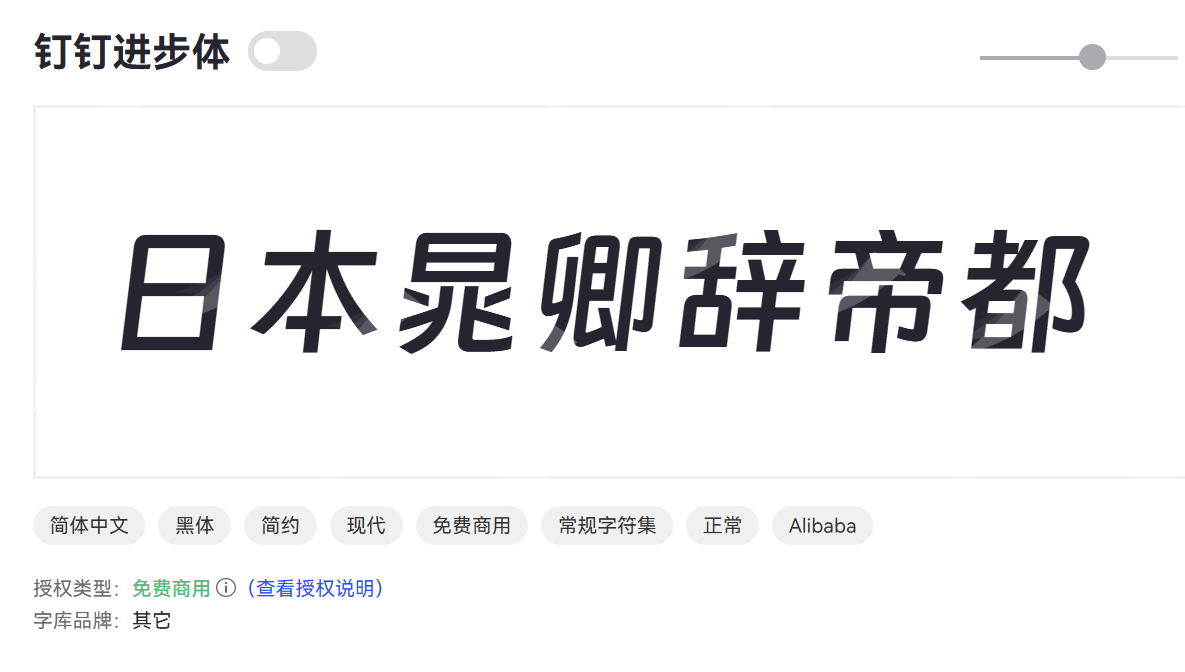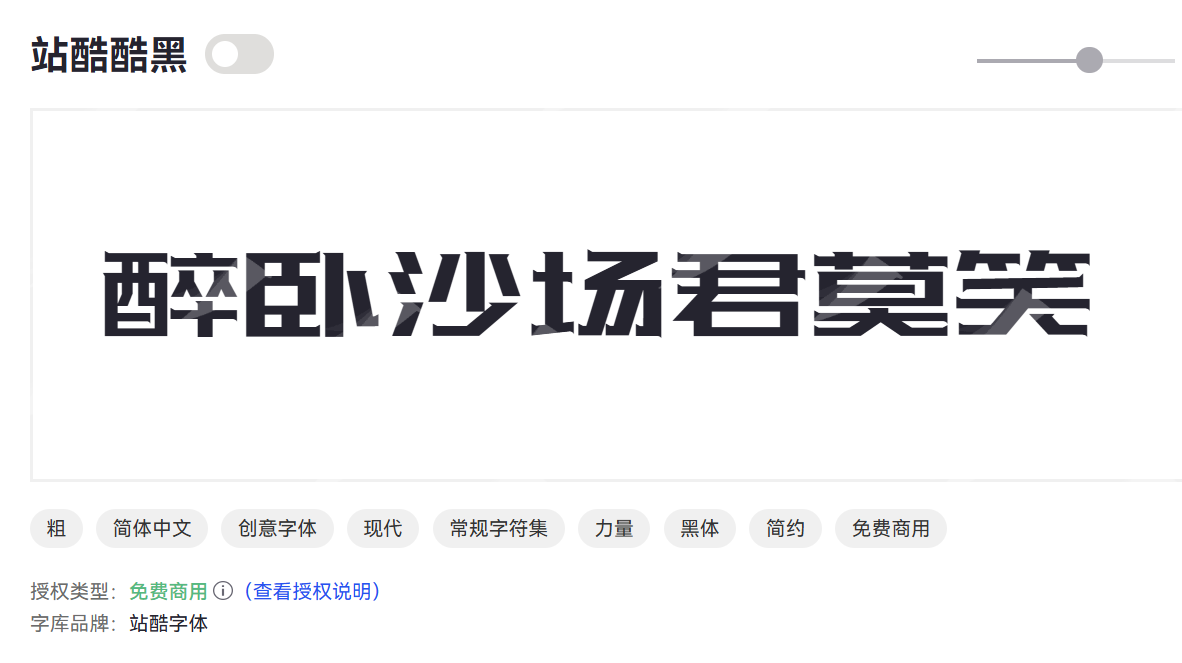
哪些字体可以免费商用,黑体、宋体、楷体的免费字体分享
在我们这个信息爆炸、内容为王的时代,无论是制作PPT、设计海报,还是运营公众号,字体都是不可或缺的视觉元素。但是,一旦涉及到“商用”,很多我们平时觉得“免费”的字体,其实都隐藏着版权的“雷区”。一旦不小心踩到,轻则收到律师函,重则面临巨额赔偿,这可真是得不偿失。今天按照字体分类,分别给大家介绍一些常用的黑体、宋体、楷体的免费字体。
可以免费商用的黑体
字由文艺黑是一款兼具现代感与艺术气息的黑体字体,线条简洁流畅,整体造型稳重而不失灵动,适合表现文艺、时尚氛围。
适合场景:文化艺术类海报与宣传、电商及时尚品牌包装设计、书籍封面、杂志排版
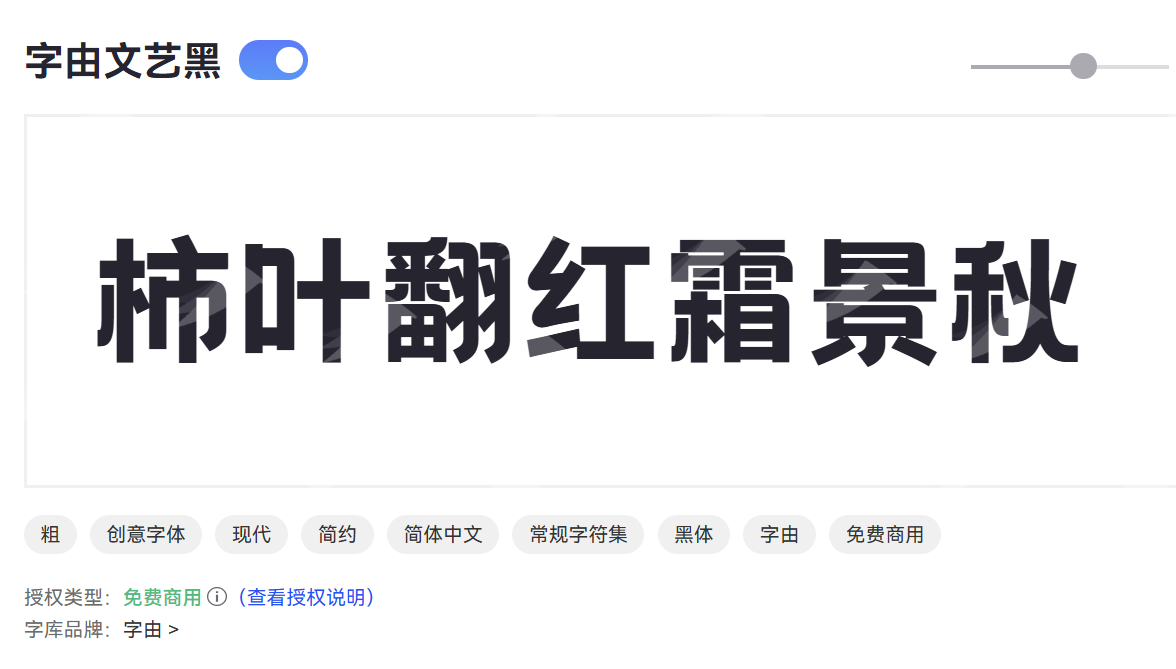
钉钉进步体
钉钉进步体由钉钉团队设计,专为数字办公和沟通场景打造,注重清晰易读与现代化风格,展现积极向上的品牌形象。
适合场景:企业品牌宣传资料、数字化办公及沟通文档、企业活动及培训资料
站酷酷黑
站酷酷黑是站酷设计团队推出的现代黑体字体,线条硬朗有力,风格时尚且富有力量感,广受设计师喜爱。
适合场景:海报及广告设计、网站大标题及LOGO设计、电子竞技与潮流文化场景、品牌视觉识别系统
可以免费商用的宋体
思源宋体
思源宋体是Adobe与Google联合开发的开源衬线字体,支持多语言,设计平衡现代与传统,适合多种文本场景。
适合场景:报刊书籍排版、学术论文与出版物、网站及App界面正文、多语言内容设计
猫啃网风雅宋
猫啃网风雅宋是一款充满韵味的宋体字体,融合了传统书法艺术与现代设计,笔触优雅自然,具有鲜明的文化气息。
适合场景:文化活动与艺术展览宣传、书籍封面与古籍排版、文创产品包装、传统文化相关品牌设计
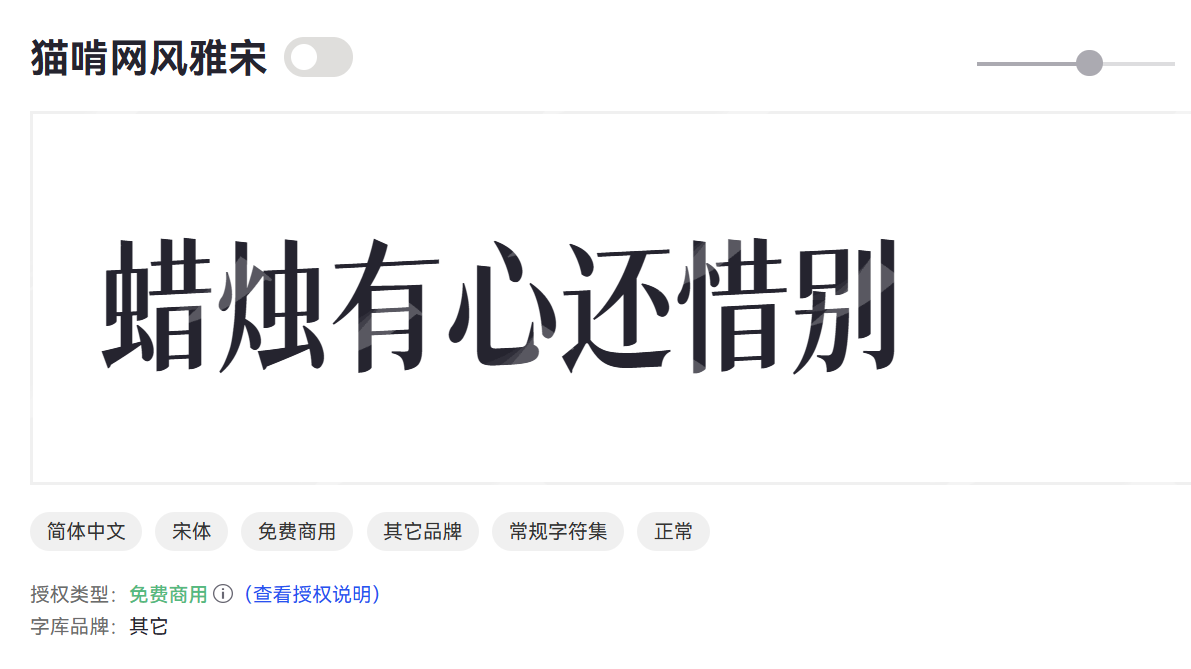
思印宋
思印宋是一款基于传统宋体的现代衬线字体,注重细节雕琢,兼具端庄与现代感,适合正式与艺术兼顾的排版需求。
适合场景:书籍和报刊正文排版、企业宣传册、高端包装设计、文化类活动及展览资料
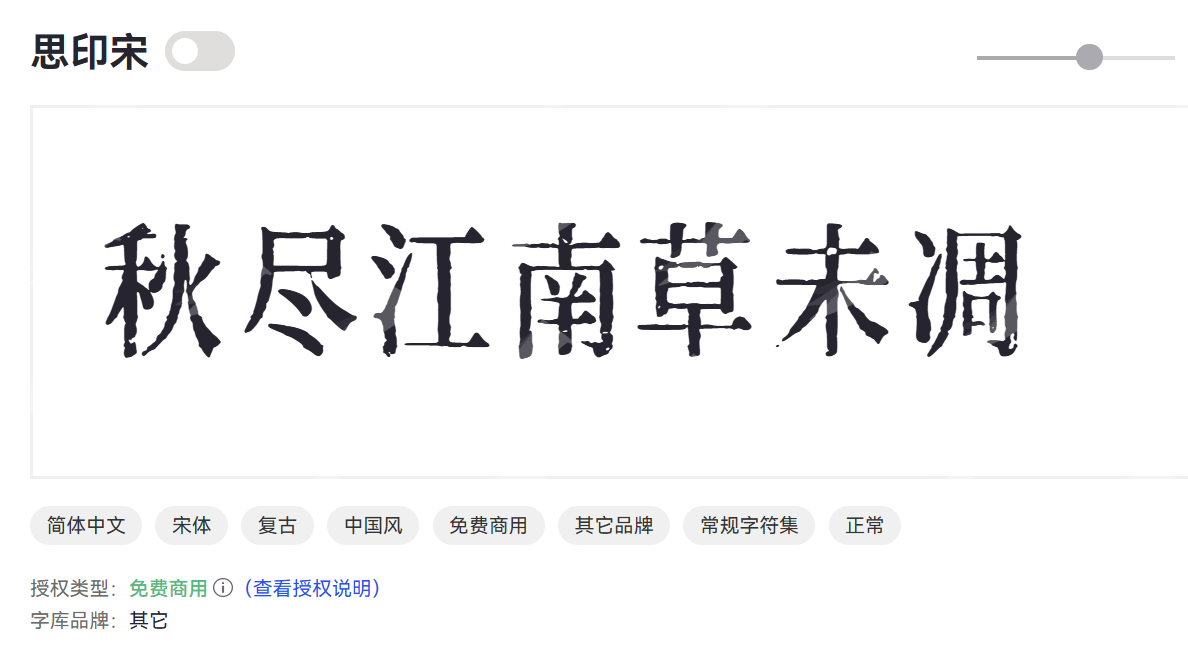
可以免费商用的楷体
江西拙楷
江西拙楷是一款仿楷书风格的字体,笔画朴拙自然,结构舒展,体现出中国传统书法的质朴与韵味。
适合场景:书法艺术作品展示、文化类海报、邀请函设计、古风主题活动
三极行楷简体
三极行楷简体是一款结合行书与楷书特征的简体字体,线条流畅自然,兼具规范与书写的灵动。
适合场景:书信、日记、手账设计、文化活动及教育宣传、品牌包装及广告文案
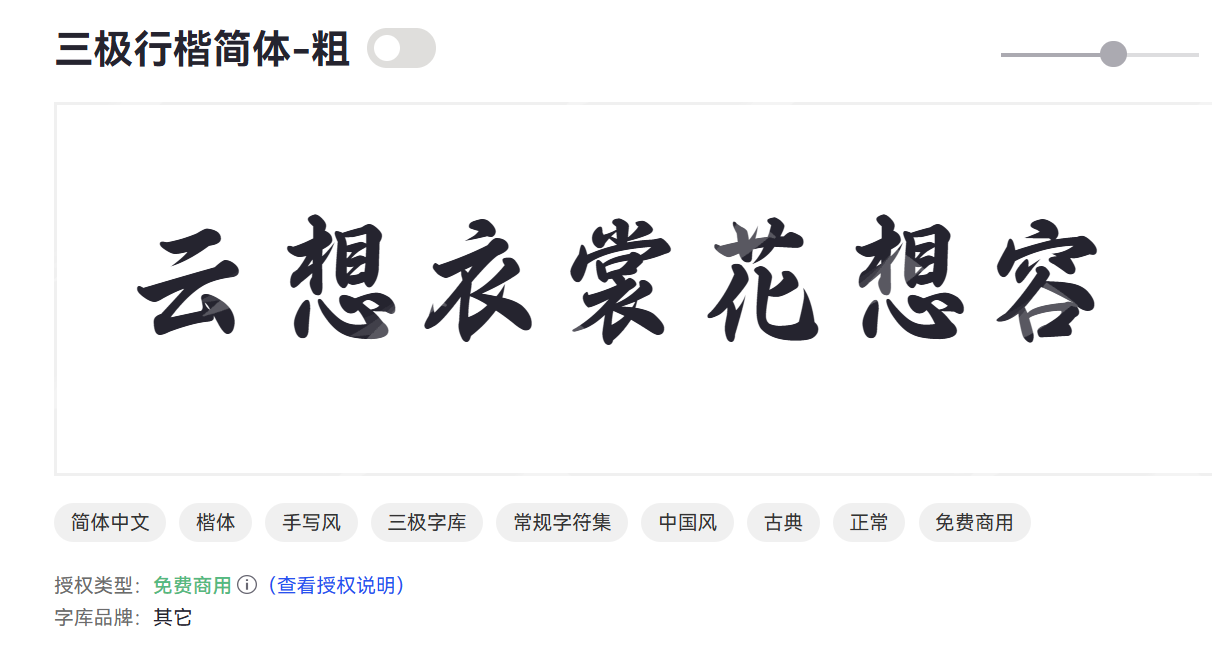
玄冬楷书
玄冬楷书是一款古朴典雅的楷书字体,笔画沉稳,结构均衡,兼具传统书法的严谨与艺术气息。
适合场景:传统文化宣传材料、礼仪请柬、证书设计、书法展览、教育出版
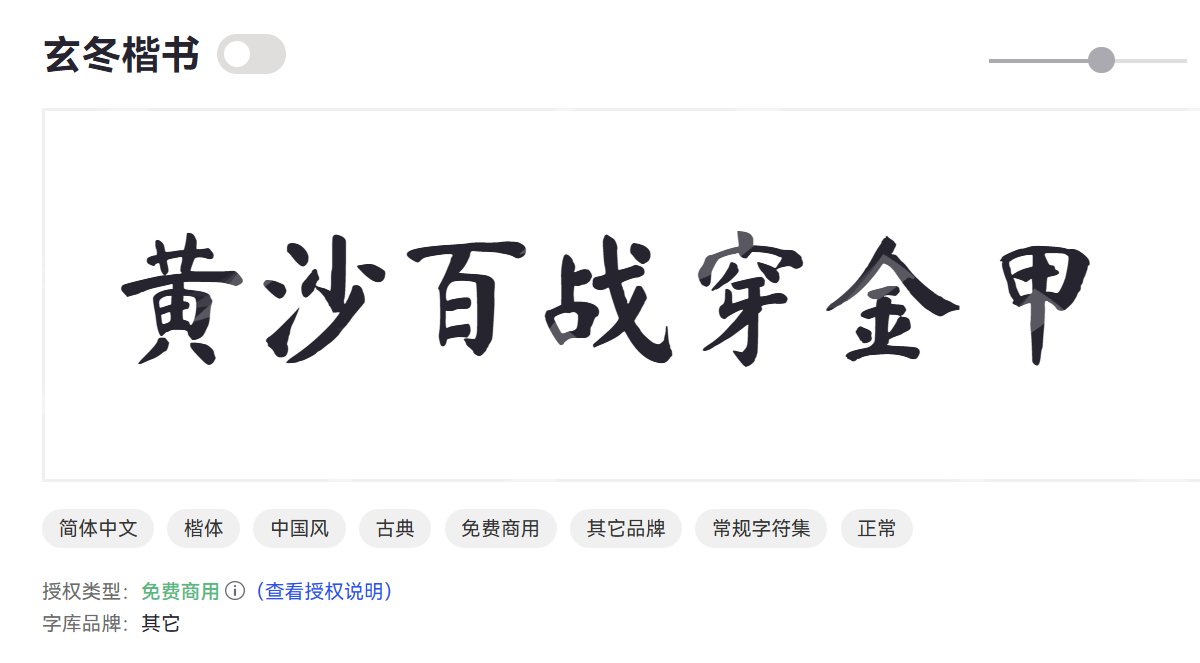
总结